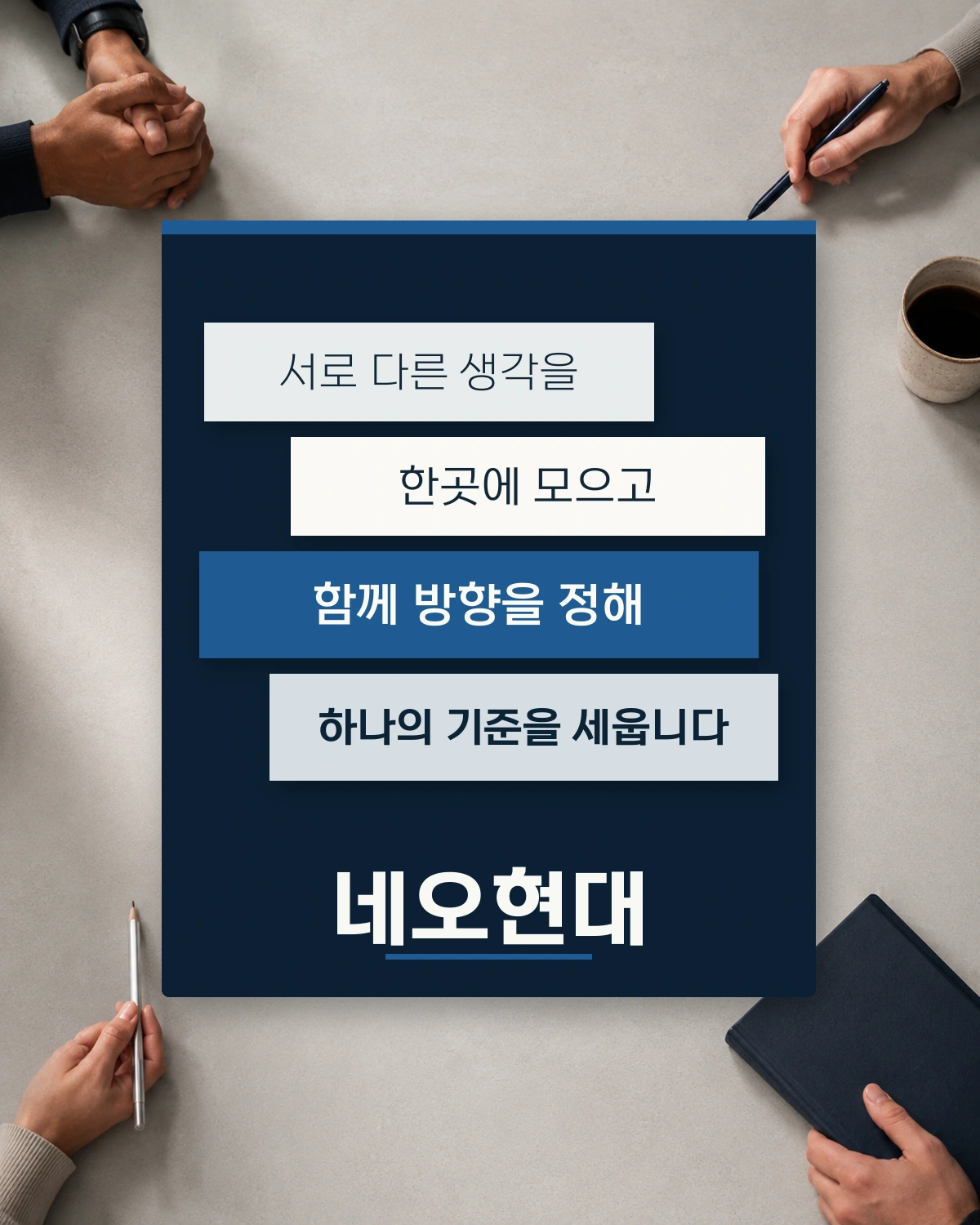
네오현대 무료폰트
네오현대 — 현대그룹에서 배포하는 무료 폰트입니다. 방향과 모양, 이름까지 임직원 의견을 모아 정한 전용 서체로, 안정감이 느껴지는 네모틀 고딕체
현대그룹이 2025년 11월에 공개한 전용 서체로 개발에 열한 달이 걸렸습니다. 만드는 과정이 특이합니다. 서체의 방향과 모양, 의미, 이름까지 중요한 단계마다 설문과 사내 공모를 거쳐 임직원들의 의견을 모아 결정했다고 밝히고 있습니다. 이름도 새로움을 뜻하는 네오와 그룹명 현대를 합친 것입니다.
제작사가 설명하는 조형은 두 축입니다. 네모틀을 가득 채운 단단한 골격이 믿음직하고 듬직한 인상을 주고, 자소와 이음줄기에는 속도감을 나타내는 곡선을 그려 넣어 도전적인 정신을 담았다는 것입니다. 온라인 환경에서 글자 왜곡을 줄인 디지털 친화적 서체라는 설명도 붙어 있습니다.
굵기는 다섯 가지로 제목용 두 종과 본문용 세 종으로 나뉩니다. 현대 한글 11,172자를 모두 담았고 계열사를 상징하는 그림문자 서른네 종이 함께 들어 있습니다. 무료로 쓸 수 있지만 수정과 개작, 재배포가 금지되고 CI나 BI, 슬로건 용도로는 쓸 수 없습니다.